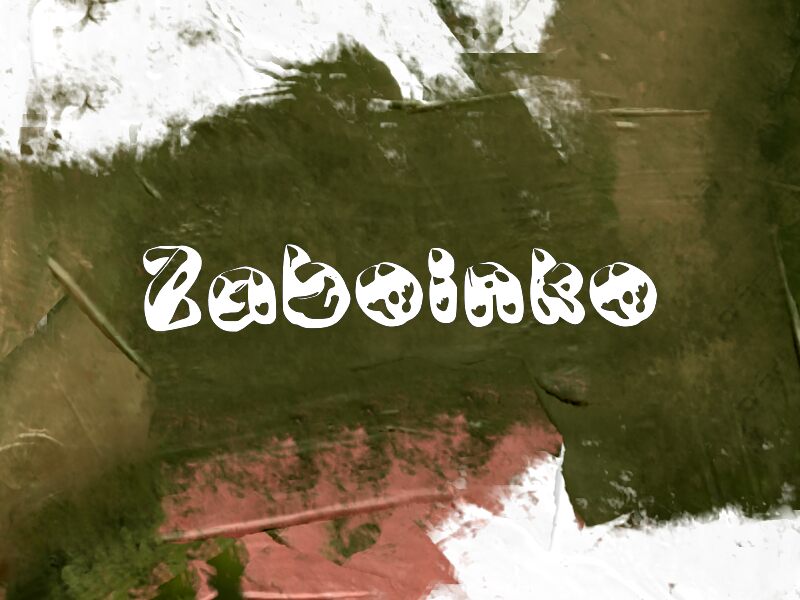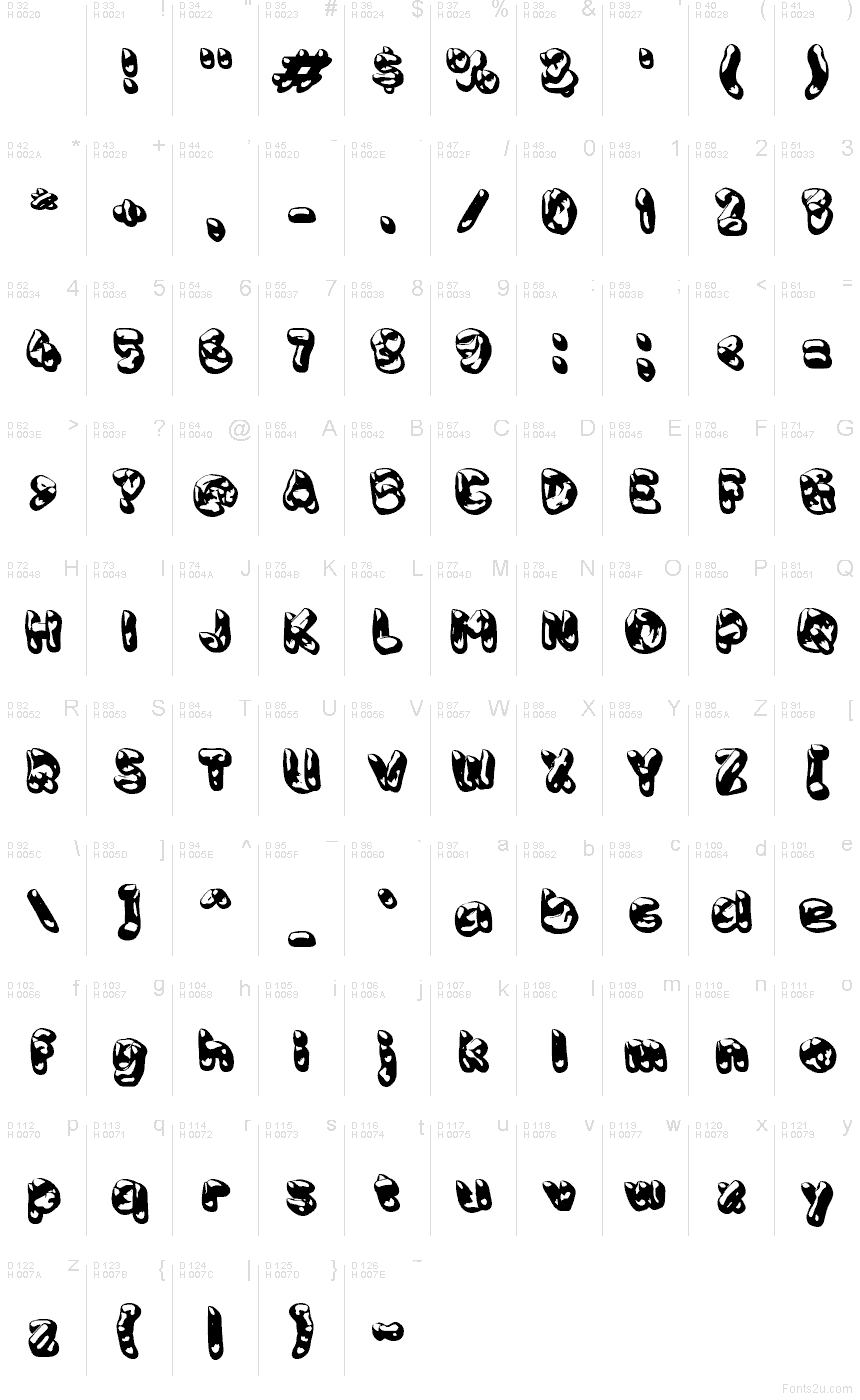
Zaboinko, créée par Wep, est une police d'affichage florale gratuite aux lettres arrondies et épaisses, qui semblent moulées plutôt que dessinées. Ses silhouettes audacieuses sont rythmées par des découpes en forme de pétales et des courbes douces, conférant à la typographie un esprit pop des années 60, presque champignon, sans jamais sacrifier sa force graphique.
Elle excelle sur les titres d'affiches, les pochettes d'albums, l'identité visuelle de cafés, le packaging et les cartons de titre, où quelques mots suffisent à donner le ton. En tant que police gratuite, Zaboinko est également idéale pour des logos, des monogrammes ou des accroches courtes : ses formes intérieures épanouies donnent aux mots les plus simples une impulsion vivante et artisanale.
Zaboinko
Présentation et spécimen de la police Zaboinko
Table des caractères de la police Zaboinko
Table des caractères de Zaboinko : Latin de base, page 1
Glyphes de la police Zaboinko — Latin de base, page 1